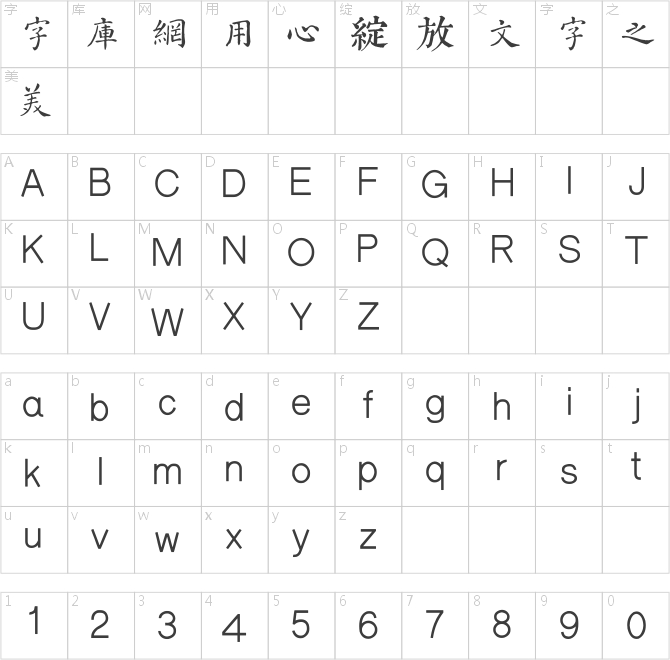
字體名稱: 邯鄲顏真卿千字
邯鄲顏真卿千字文
邯鄲顏真卿千字文字體下載邯鄲(唐)顏真卿千字文
顏真卿(709年-784年8月23日),字清臣,小名羨門子,別號(hào)應(yīng)方,京兆萬年(今陜西省西安市)人 ,祖籍瑯玡臨沂(今山東省臨沂市)。唐朝名臣、書法家,秘書監(jiān)顏師古五世從孫 、司徒顏杲卿從弟。
開元二十二年(734年),顏真卿登進(jìn)士第,歷任監(jiān)察御史、殿中侍御史。后因得罪權(quán)臣楊國(guó)忠,被貶為平原太守,世稱“顏平原”。安史之亂時(shí),顏真卿率義軍對(duì)抗叛軍。后至鳳翔,被授為憲部尚書。唐代宗時(shí)官至吏部尚書、太子太師,封魯郡公,人稱“顏魯公”。興元元年(784年),被派遣曉諭叛將李希烈,凜然拒賊,終被縊殺。他遇害后,嗣曹王李皋及三軍將士皆為之痛哭。追贈(zèng)司徒,謚號(hào)“文忠”。
顏真卿書法精妙,擅長(zhǎng)行、楷。初學(xué)褚遂良,后師從張旭,得其筆法。其正楷端莊雄偉,行書氣勢(shì)遒勁,創(chuàng)“顏體”楷書,對(duì)后世影響很大。與趙孟頫、柳公權(quán)、歐陽詢并稱為“楷書四大家”。又與柳公權(quán)并稱“顏柳”,被稱為“顏筋柳骨”。又善詩文,有《韻海鏡源》、《禮樂集》、《吳興集》、《廬陵集》、《臨川集》,均佚。宋人輯有《顏魯公集》。